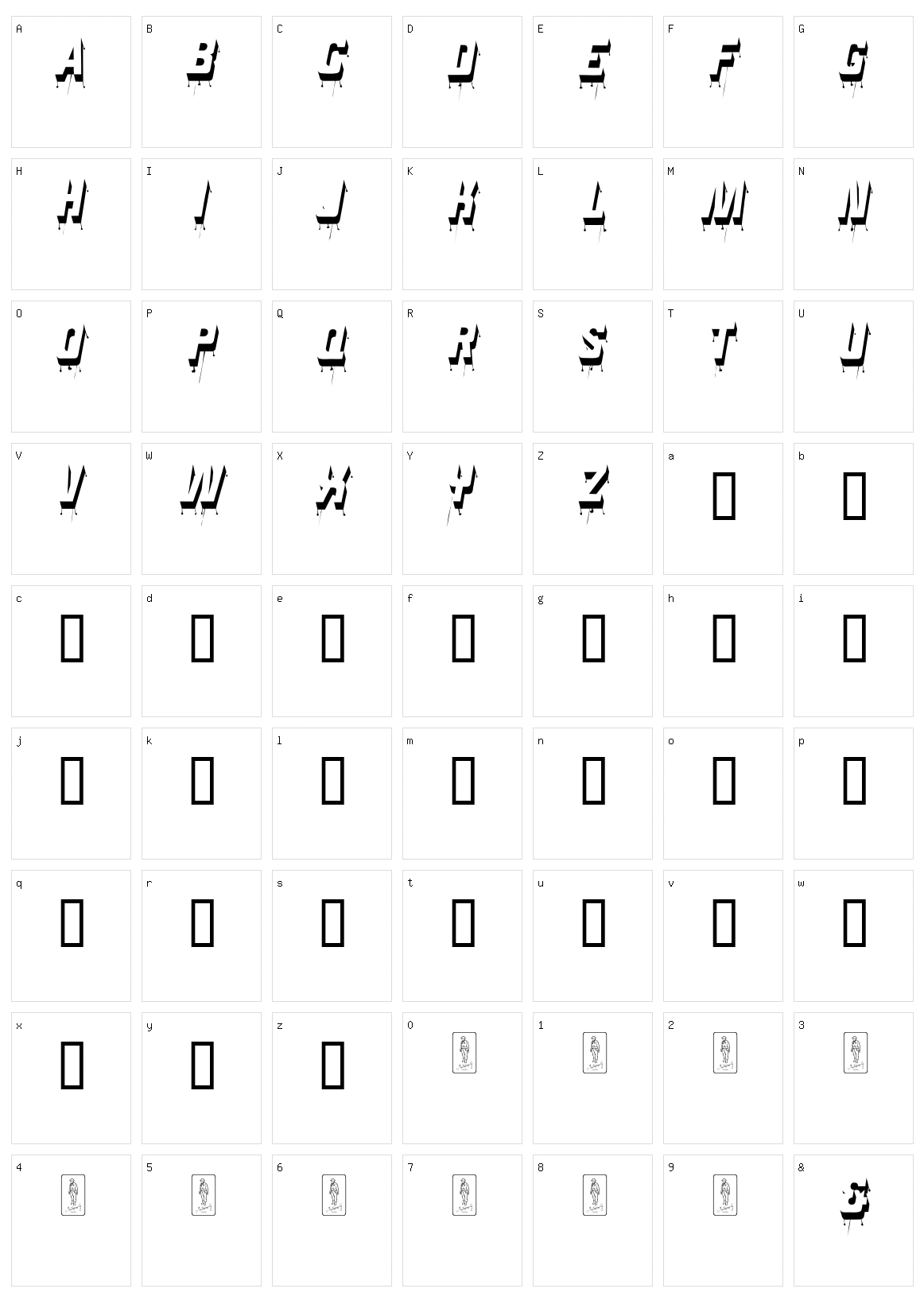
"Venerada" es una fuente gratuita de MatreroG fuentes.
Venerada inspirada en un viejo cartel de pizzeria en
Avellaneda, sobre la avenida Belgrano. En un principio
fue solo un trabajo práctico en la universidad, pero
luego se tranformo en está familia tipografica.
Venerada is inspired on a pizza-shop show-bill in
Belgrano aveneu, Avellaneda. At first it was only
a university work, But then change in this typeface.